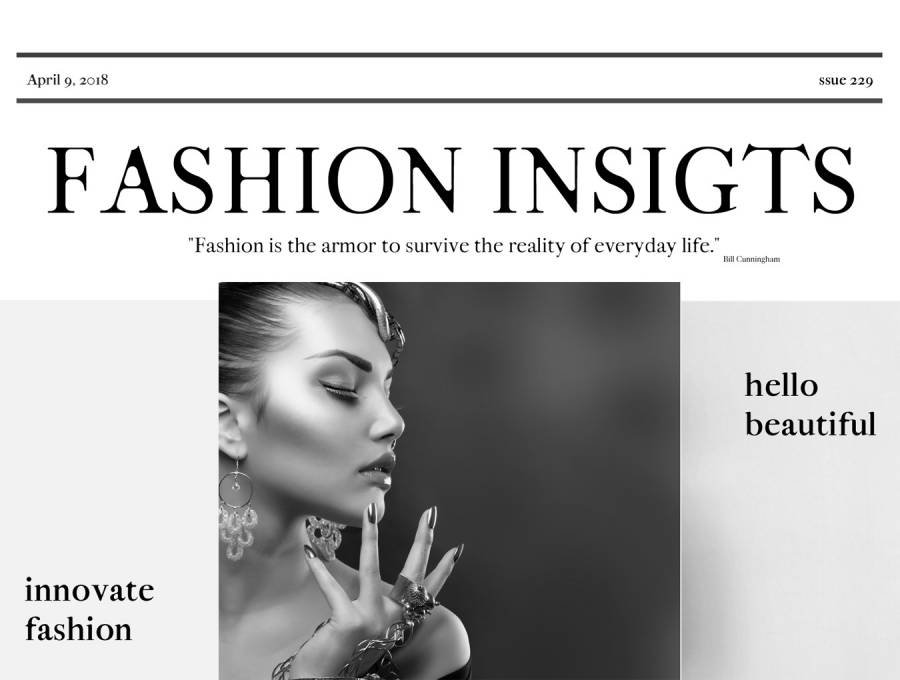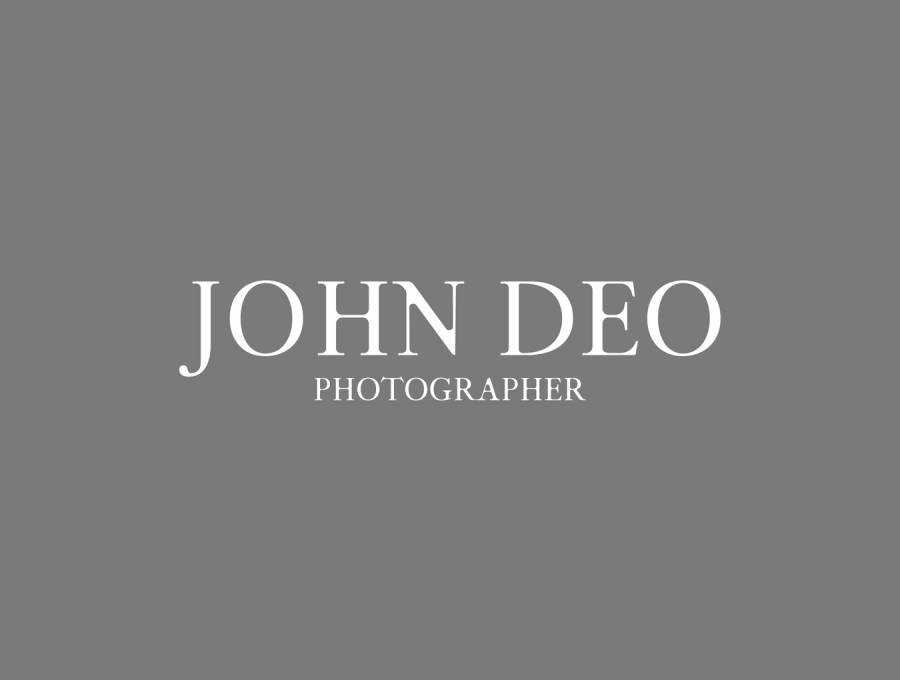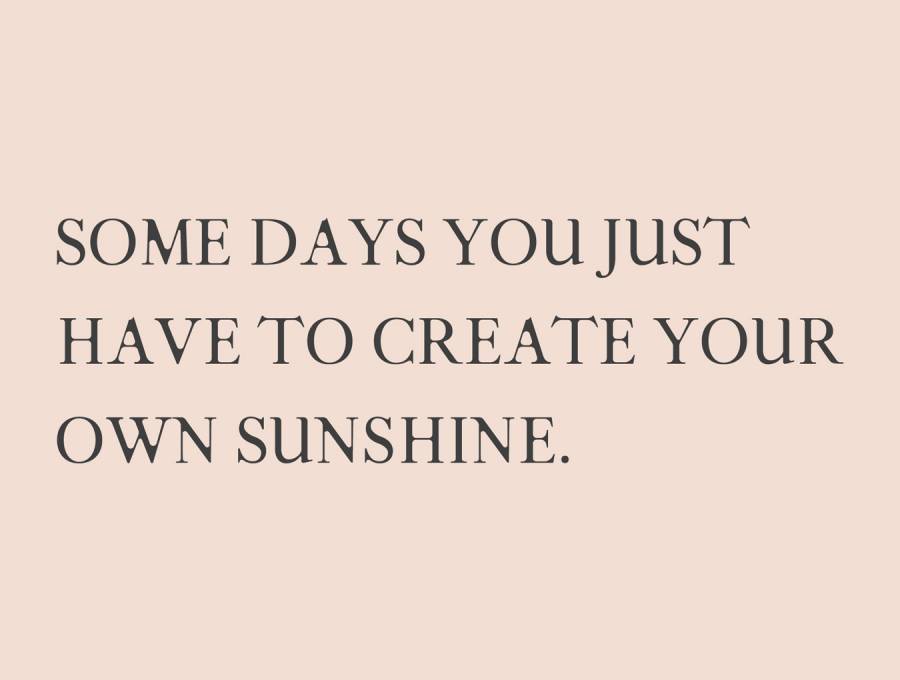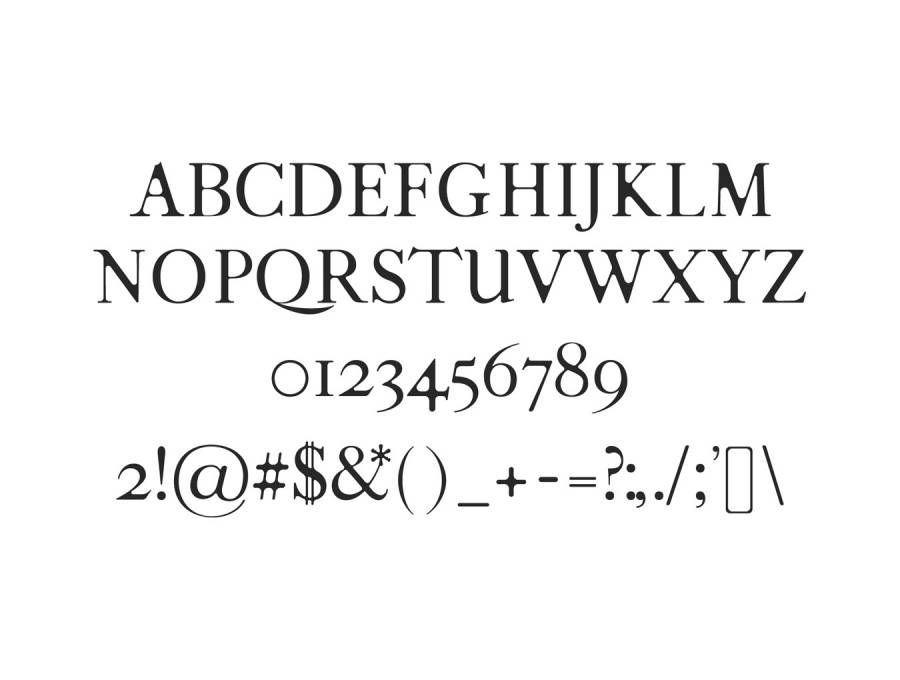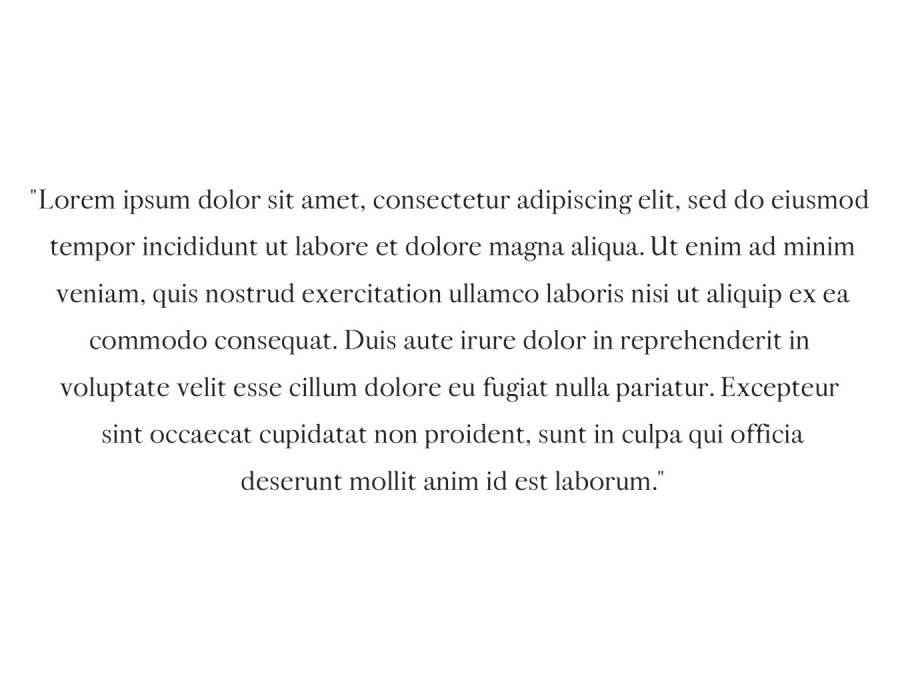
Moises Serif 3字体重量家庭装。,Moises Serif字体系列
Moisses Serif Font Family是一种简单的圆形衬线字体。它有3个重量。每个重量包括所有具有非英语字符的基本gylphs。 Moisses对于演示文稿,海报,杂志,标题,名片,杂志,网页布局,邀请函,标识,书籍,标题,品牌以及几乎任何创意设计都非常有用。